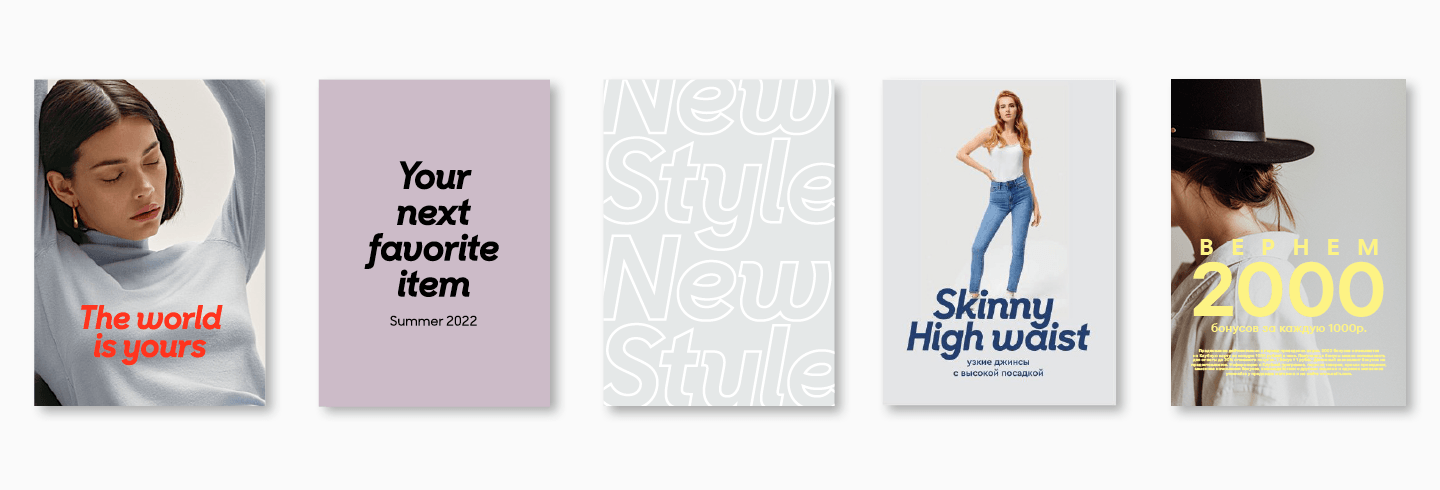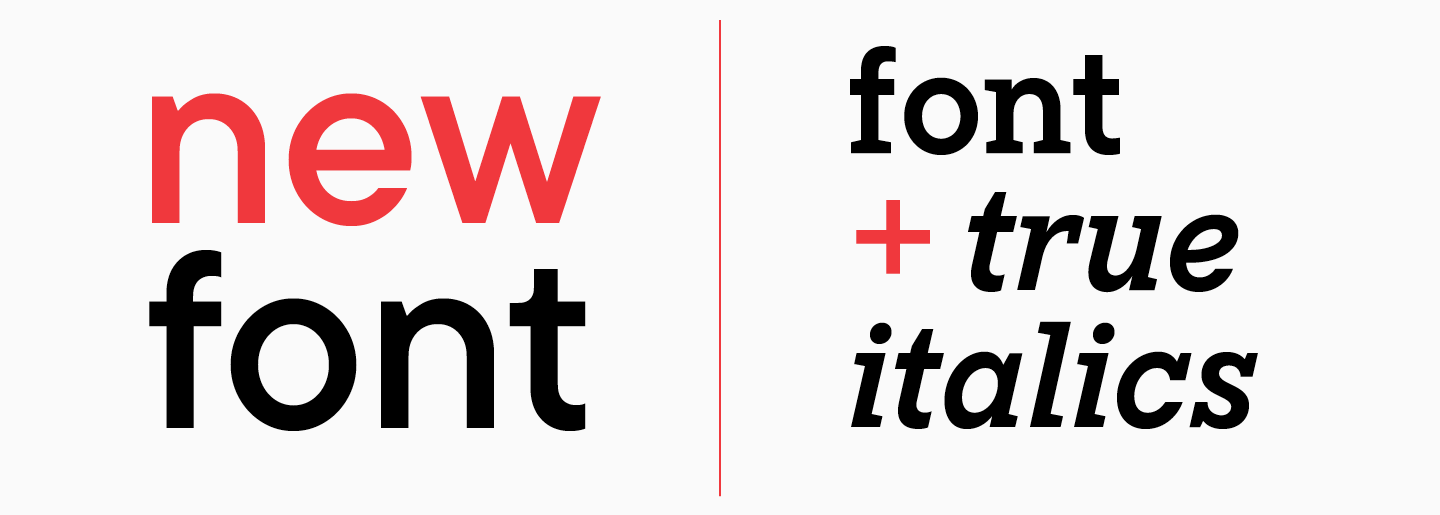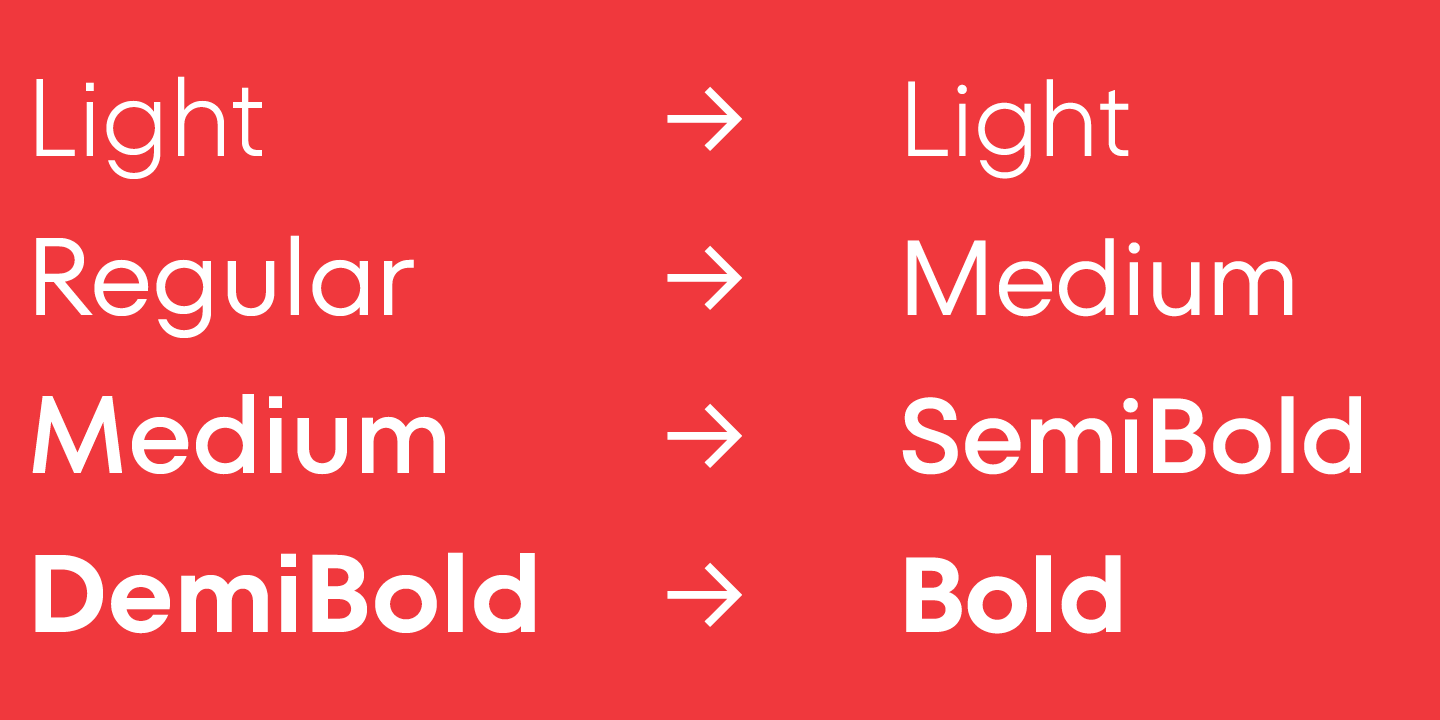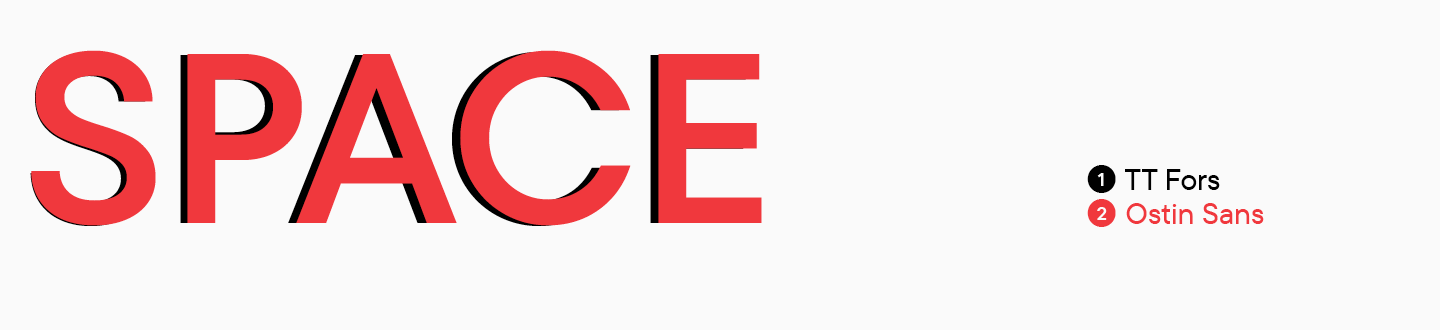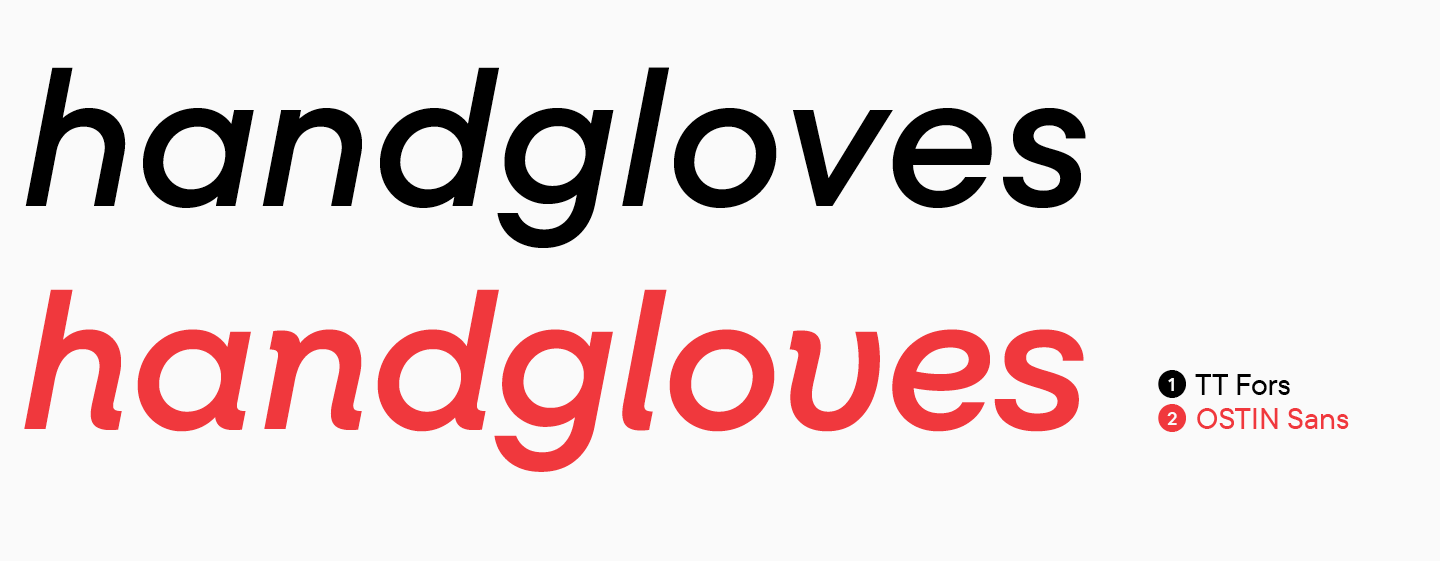
O’STIN — популярный российский бренд одежды и аксессуаров в стиле сasual. Покупатели полюбили O’STIN за разнообразие ассортимента и доступную ценовую политику.
К моменту, когда команда O’STIN обратилась к нам за фирменной гарнитурой, концептуальная часть ребрендинга была готова. Целью всех изменений было привлечение новой аудитории при сохранении существующей.
Многие знают O’STIN как удобные и практичные вещи, ориентируясь на рациональные факторы. Бренду хотелось стать привлекательнее и для тех, кто при выборе одежды ориентируется на эмоциональные характеристики бренда. Практичные и повседневные вещи — это здорово, но из них можно создавать уникальные образы для разных ситуаций.
Обсуждение концепции
Шрифту отводилась ведущая роль в обновлении фирменного стиля. Уже на предварительном этапе стало понятно, что гарнитура должна включать и прямые начертания, и италики. Такой подход отвечал запросам ребрендинга: прямой и строгий гротеск комфортно воспринимается рациональной аудиторией, в то время как динамичные и яркие италики могли привлечь внимание эмоциональной.
Стоит пояснить, что речь идёт о настоящих италиках, то есть курсивах, а не о наклонённых шрифтах. Отличие в том, что в наклонных начертаниях в буквах не меняются конструкции, в то время как настоящие италики представляют собой отдельный шрифт с заново нарисованными формами знаков. Настоящие италики представлены в таких шрифтах студии TypeType, как TT Livret или TT Rationalist.
Нам предстояло понять, как концепция двух шрифтов в фирменном стиле может работать на бренд, насколько этот подход отвечает выбранным целям и что мы, как студия, можем предложить со своей стороны.
Прежде всего, наша команда предложила O’STIN две стратегии работы, каждая из которых обладала преимуществами.
- В первом случае мы могли разработать абсолютно новый шрифт с нуля. Это трудоёмкий процесс, занимающий больше времени, однако в результате получается уникальная гарнитура.
- Во втором варианте мы предложили выбрать гротеск из коллекции TypeType, который подходит по основным запросам, и кастомизировать его. В этом случае также предстоит нарисовать италики, ведь во всех гротесках студии используются наклонные начертания без изменения конструкций знаков, а не курсивы. Такой вариант требует меньше ресурсов, что ускоряет процесс работы, однако финальный шрифт базируется на уже существующем тиражном шрифте.
После долгих обсуждений, остановились на втором варианте. С этого момента началась работа над фирменным шрифтом O’STIN.
Исследовательская часть
Любой шрифт TypeType начинается с исследования. На этом этапе мы собираем всю информацию о будущей гарнитуре, анализируем конкурентов и решаем, каким будет финальный состав шрифта.
На этапе исследований для шрифта O’STIN нам предстояло выяснить:
- действительно ли использование прямых начертаний гротеска и настоящих италиков поможет достичь поставленной цели: привлечь новую аудиторию, сохранив старую;
- гротеск какой категории стоит выбрать;
- какой шрифт из коллекции TypeType лучше подойдёт в качестве основы для фирменного шрифта O’STIN.
Команда O’STIN предоставила нам подробный срез рынка. Бренды конкурентов, попавшие в подборку, можно было разделить на две группы: привлекающие внимание рациональной аудитории и располагающие к себе эмоциональную. Эту информацию мы взяли за основу собственного исследования.
Проанализировав фирменный стиль компаний, заостряя внимание на типографике, мы нашли определенные закономерности.
- Шрифты для брендов рациональной части рынка были исключительно функциональными. Это логичное решение, ведь в данном случае гарнитура должна в первую очередь доносить информацию о компании и её продукции. Шрифт в таком подходе может не выступать частью фирменного стиля и не ассоциироваться с брендом напрямую. Более того, многие бренды этого сегмента могут использовать разные гарнитуры в коммуникациях, выбирать шрифт под определенную задачу. Например, рассказать о скидках, проинформировать о новой коллекции, поделиться новостями о компании. В качестве основной гарнитуры чаще встречаются неогротески, хотя в таких случаях не всегда можно выделить главный шрифт.
Эмоциональный сегмент рынка относится к шрифту иначе. Гарнитура таких компаний отвечает за ассоциации с брендом, транслирует его ценности и взгляды. Фирменный шрифт при этом может обладать относительно нейтральным характером с оттенком чего-то ещё, а не быть ярким и вызывающим. Это связано с тем, что гарнитура по-прежнему передаёт информацию и не должна мешать восприятию, вызывая эмоциональные ассоциации скорее бессознательно. Такой шрифт — связующее звено всех коммуникаций бренда. Сам факт наличия фирменного шрифта, передающего характер компании, сдвигает бренд в сторону эмоциональной аудитории. Любопытно, что в этом сегменте популярны геометрические гротески.
Эти выводы помогли нам осознать, что сам факт наличия фирменного шрифтового семейства переведёт бренд O’STIN в более эмоциональную категорию. Тем более, если это будет геометрический гротеск. Использование настоящих италиков позволит придать характеру коммуникаций более выраженный оттенок.
Предстояло выбрать шрифт из коллекции TypeType, на основе которого будет создаваться корпоративная гарнитура. Главных претендентов оказалось два: TT Fors и TT Chocolates. Мнения по поводу кандидатов разделились, поэтому был проведён внутренний опрос среди дизайнеров и тех, кто не связан с шрифтовой индустрией. Им предстояло описать предложенный шрифт тремя эпитетами.
Разработка Ostin Sans заняла 3 месяца. Это достаточно короткий срок для создания фирменной гарнитуры, в который нам удалось уложиться благодаря отточенному процессу создания больших шрифтовых семейств и слаженной команде.
В процессе работы проект приобрел новый оттенок и стал самостоятельным, изящным и уникальным шрифтом. С помощью италиков нам удалось решить не только типографическую, но и стратегическую маркетинговую задачу O’STIN. Мы благодарны команде O’STIN за оказанное доверие.